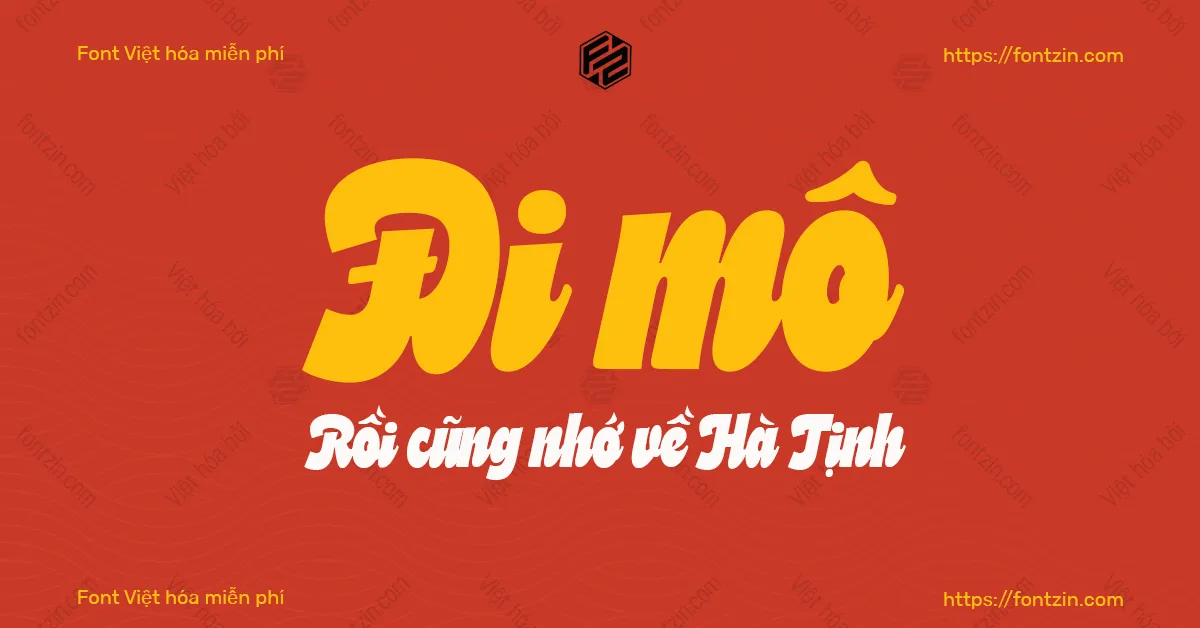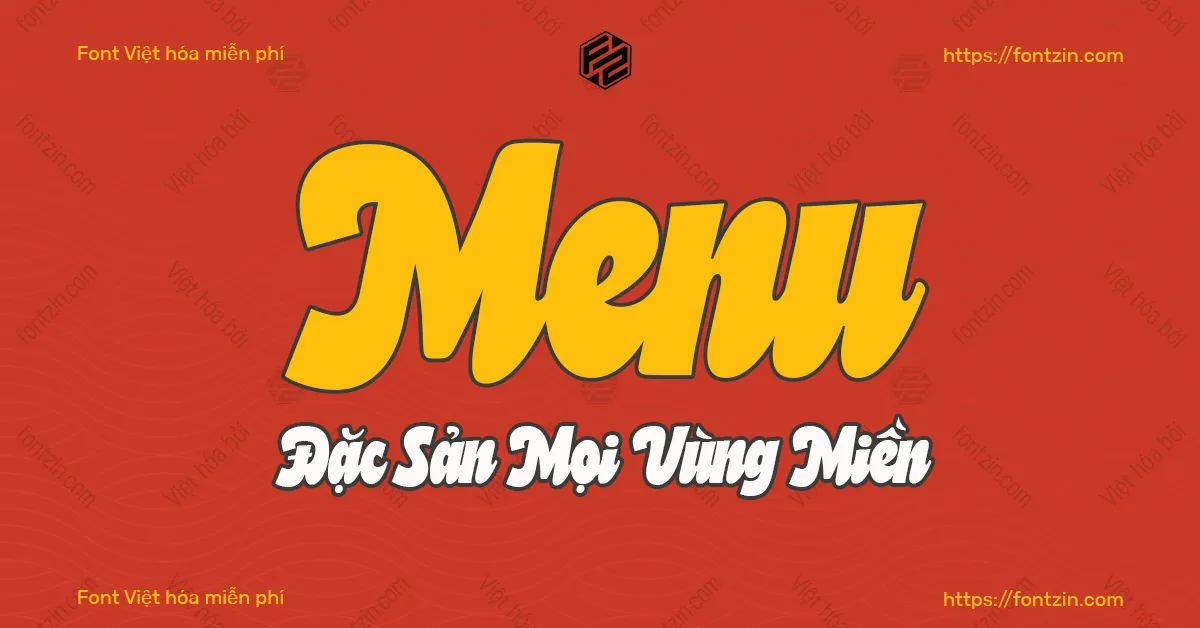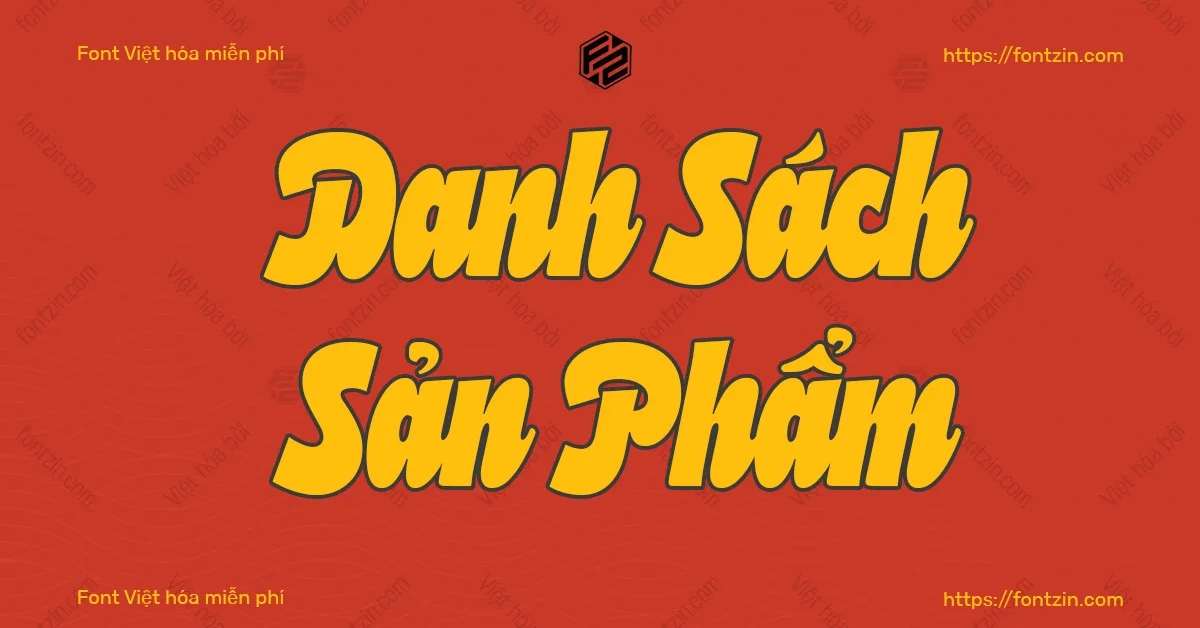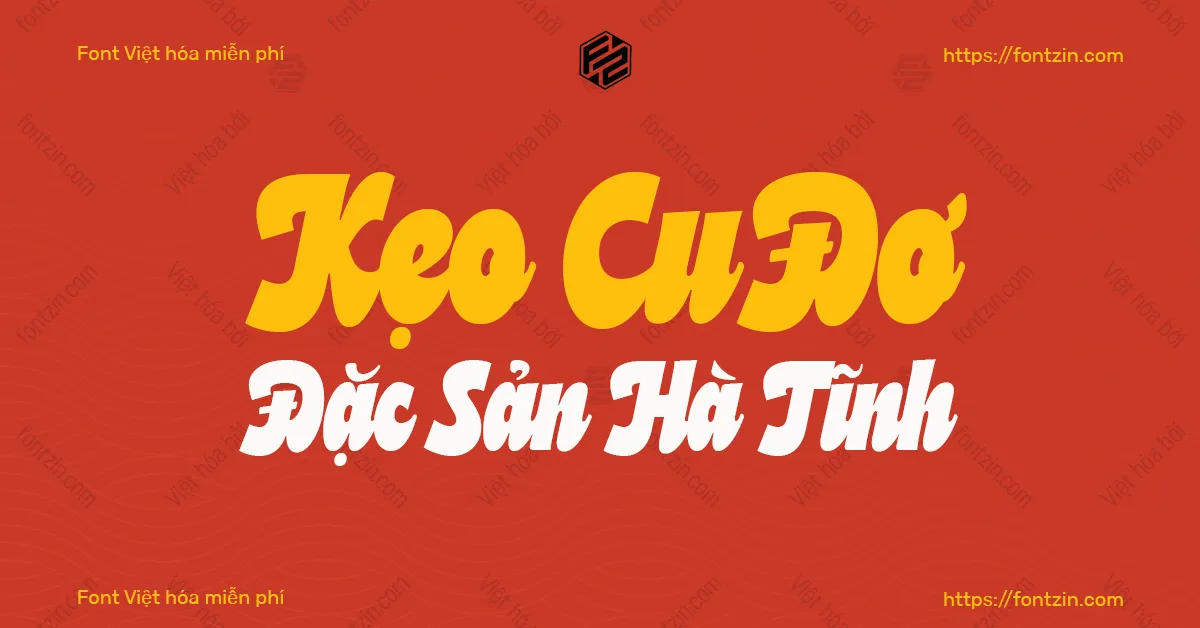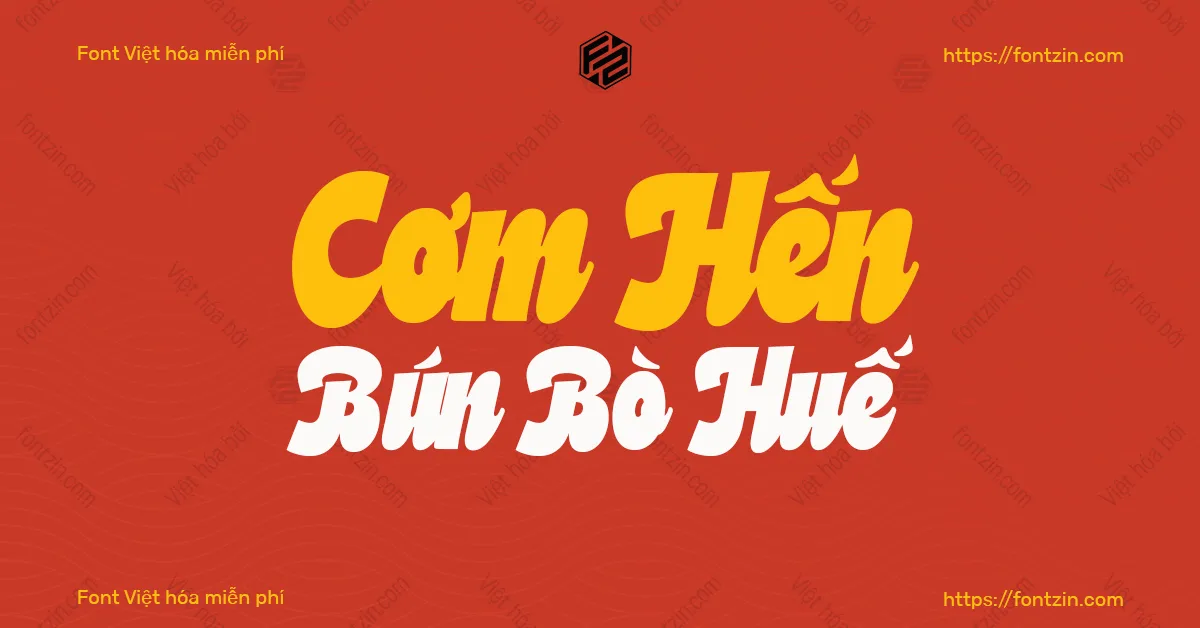
Font chữ Retro Việt hóa
Tải Font chữ Retro Việt hóa – Nét đẹp hoài cổ, siêu đẹp
Font chữ Retro Việt Hóa là sự kết hợp hoàn hảo giữa nét đẹp hoài cổ và tính thẩm mỹ hiện đại, mang đến cảm giác thân thuộc nhưng không kém phần nổi bật. Lấy cảm hứng từ các thập kỷ trước, phông chữ Retro mang đậm dấu ấn của các thiết kế cổ điển, với những đường nét tinh tế, mềm mại và hài hòa. Đây là sự lựa chọn lý tưởng cho những dự án muốn tái hiện vẻ đẹp vượt thời gian và tạo dấu ấn khác biệt.
Font Retro Việt Hóa hỗ trợ đầy đủ các ký tự tiếng Việt, giúp bạn dễ dàng sử dụng trong các dự án sáng tạo như thiết kế poster, bìa sách, banner quảng cáo, hay các sản phẩm liên quan đến thời trang, âm nhạc, hoặc văn hóa đại chúng. Với nét chữ đầy cảm xúc và quyến rũ, phông chữ này không chỉ gợi lên cảm giác hoài niệm mà còn giúp nội dung trở nên cuốn hút và phong cách.